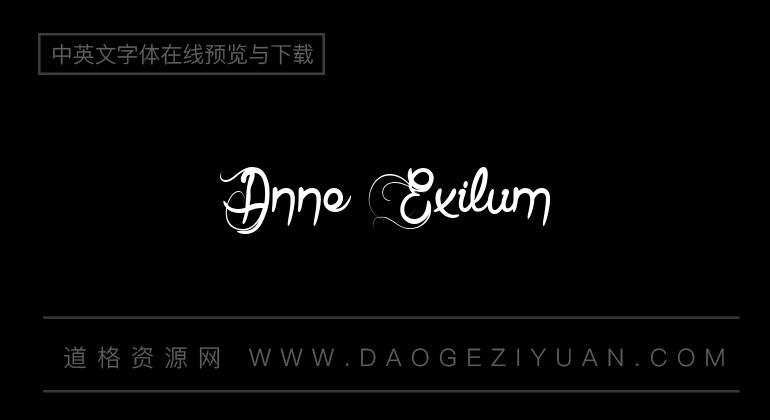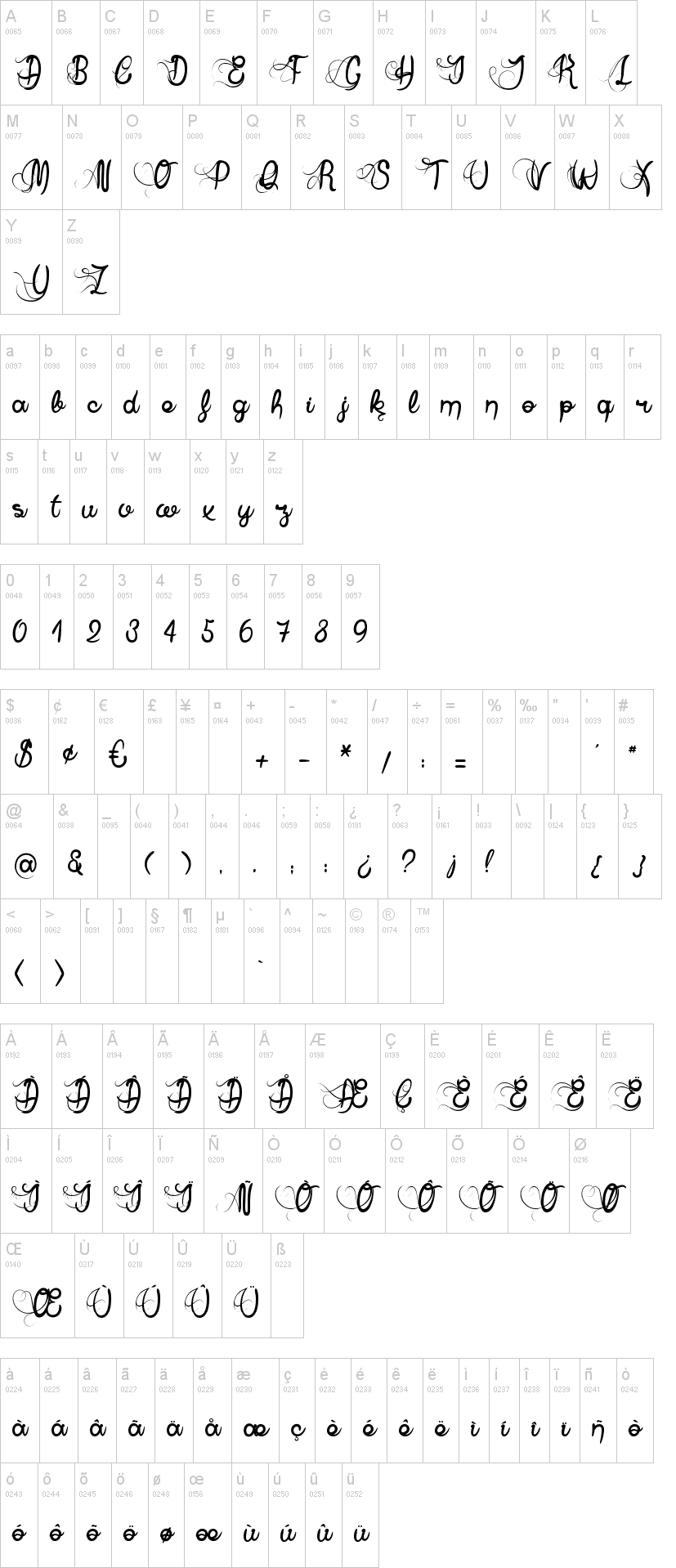
? Anne Exilum 字体是一款设计精美的英文字体,由Anne Smith设计发布,它具有独特的手写风格,每个字母都有细节处理,使字体看起来更加立体,更有趣味性。它具有轻盈的笔触,可以让你的文字看起来更加清晰,更有活力。Anne Exilum字体可以用于商业和个人用途,可以应用于海报、广告、网站等各种场景。内容介绍
Anne Exilum是一款非常不错的手写艺术字体,具有很好的视觉感,适合于文化类的宣传设计、商业类品牌的广告和产品包装设计以及个性化文字排版等较多场景。